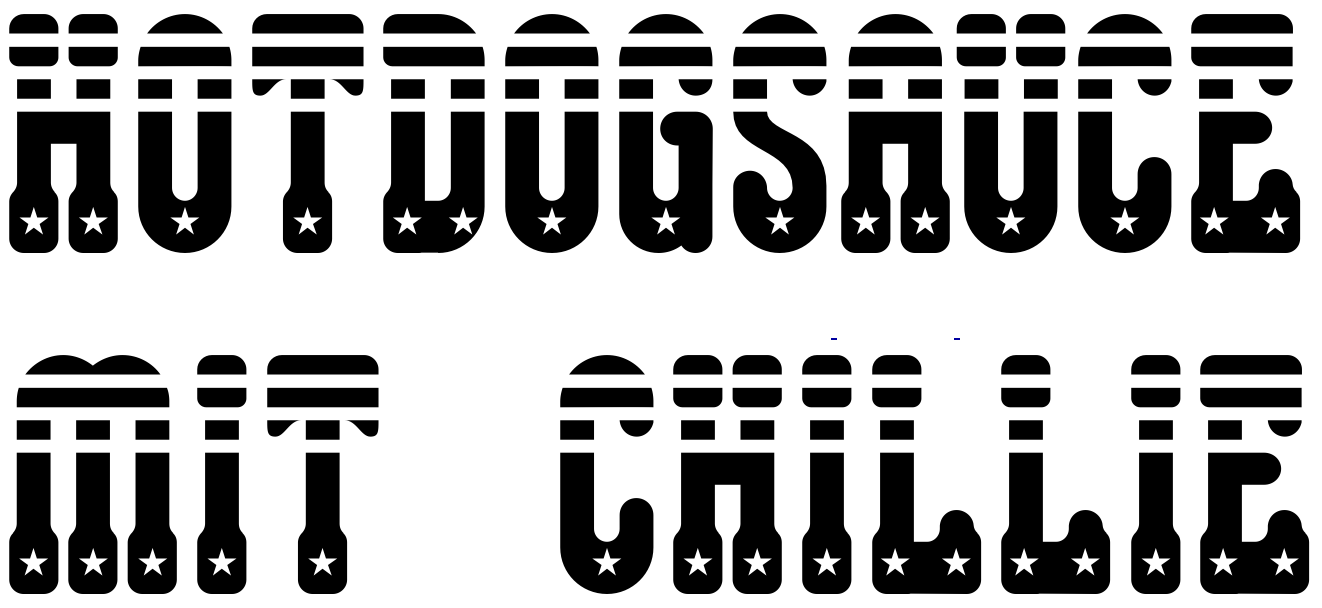
Suche diese Schriftart aus den 70/80er Jahren (Hotdog)
Hallo...ich arbeite gerade an einem Projekt und möchte diese Schriftart verwenden bzw. mir fehlende Buchstaben ergänzen. Das Bild wurde damals von mir gemacht- es stammt von einem Hotdogladen unserer Stadt aus den Ende 70er- Anfang 80er Jahren.
Da es damals sicherlich computermäßig noch nicht so viele Möglichkeiten gab stellt sich mir die Frage, ob diese Schriftart selbst gemacht wurde oder nicht...wenn ja: gibt es eine Schriftart, die dieser sehr nahe kommt und die man modifizieren kann?
Richtig,
mit den Computerfonts, so wir diese heute nutzen war es damals noch gaaaanz am Anfang, und damals ging es mit Peter Karow und Ikarus erst gerade los, klassische Bleisatzschriften zu digitalisieren.
Allerdings gab es seit 1972 mit dem HP-Stiftplotter HP-8972 die Möglichkeit auch Klebefolien zu schneiden, und dafür eben auch CAD-Programme,wie danals von Autocad die abgespeckte CAD Software Autosketch zu verwenden. Somit konnten dann saubere Reklamebeschiftungen für Autos, Ladenschilder und damals auch oft Schaufenster von Leuten erstellt werden, die nicht mehr diese ruhige Hand eines echten Schildermalers hatten.
Die "Fonts" von damals war dann nicht eine zusammenhängige Schriftdatei, sonderen Sammlungen der ganzen Buchstaben, Ziffern und nötigsten  Satzzeichen einer Schriftart, jede Glyphe einzeln als HPGL oder DXF-Datei. Da war dann eben ein Font eine Diskette mit vielleicht 30 bis 40 Glyphen, die dann als a.dxf bis z.dxf, one.dxf bis nine.dxf , period.dxf, comma.dxf. exclam.dxf und so weiter hießen.
Diese Dateien mussten dann eben in die CAD-Zeichnung der Beschriftung einzeln importiert und platziert werden.
Ich glaube, ich hatte noch ziemlich lange eine 5 1/4"-Diskette mit so einem Zeichensatz herum(f)liegen, die dann, weil unlesbar geworden zusammen mit all den alten Floppys entsorgt wurde.
Als dann CorelDRAW mit den ersten Vektorschriften im eigenen *.wmf-Format heraus kam, und diese Software von anfang an einen gut funktuonierenden HPGL-Plotausgabefilter hatte, und man so die Texte dann einfach als gewönlichen Text eintippen kommte, wechselten die Schilder-Plotterer sehr viel hier hin, und die CAD-Buchstaben gerieten in Vergessenheit, bis sie irgendwann einfach entsorgt wurden, da die hier gespeicherten Schriften auch nicht mehr dem Zeitgeschmack entsprachen. Die Schriften des ersten CorelDRAW waren dann wirklich inflationär für Folienbeschriftungen in Gebauch und jede neue Imbissbude schrieb sich in Arnold Böcklin.
Ich denke, die von Dir vorgestellte Beschriftung wird auch so etwas aus der digitalen Steinzeit sein, und um ein neu zeichnen wird man kaum herum kommen, schon einige meiner Schriftarten sind ja so entstanden. (was natürlich leichter währe, hätte man diese alten CAD-Zeichnungen noch)
Ich würde ja sowas* nehmen und die Streifen und Sterne händisch basteln …
Wird ja kein langer Text sein, der damit gesetzt werden soll :-?
* Nur schnell nach einer Rounded Egyptienne gesucht, findet man vielleicht auch passenderes, bei MyFonts oder so …
Und hier mal ein Zwischenstand von mir. X und ẞ machen mir noch kopfzerbrechen, Ziffern und Satzzeichen fehlen auch noch, und dann gibt es dann noch Layer-Versionen mit nur dem Stipes Teil und nur dem, mit den Sternchen drin, auch plane ich ne Version mit schraffierten oberen Teil.
Das ich mich an diese Schrift heran gemacht habe, liegt einfach daran, dass die bei mir so viele Erinnerungen geweckt hat, war es doch eine Zeit, in der ein normaler Mensch bestenfalls einen VC20 , oder an irgend ner Uni eine AIM65 zu gesicht bekam, und Schriften waren da eben Pixelschiften, und dann sah man pöätzlich an jedem Schaufenster Folienbeschritungen. Und so erinnerte ich mich an den Missbrauch von Software, die für Konstrukteure gedacht war, aber von der Beschrifterbranche - mit reichlich Verschuldung - dafür verwendet wurde.